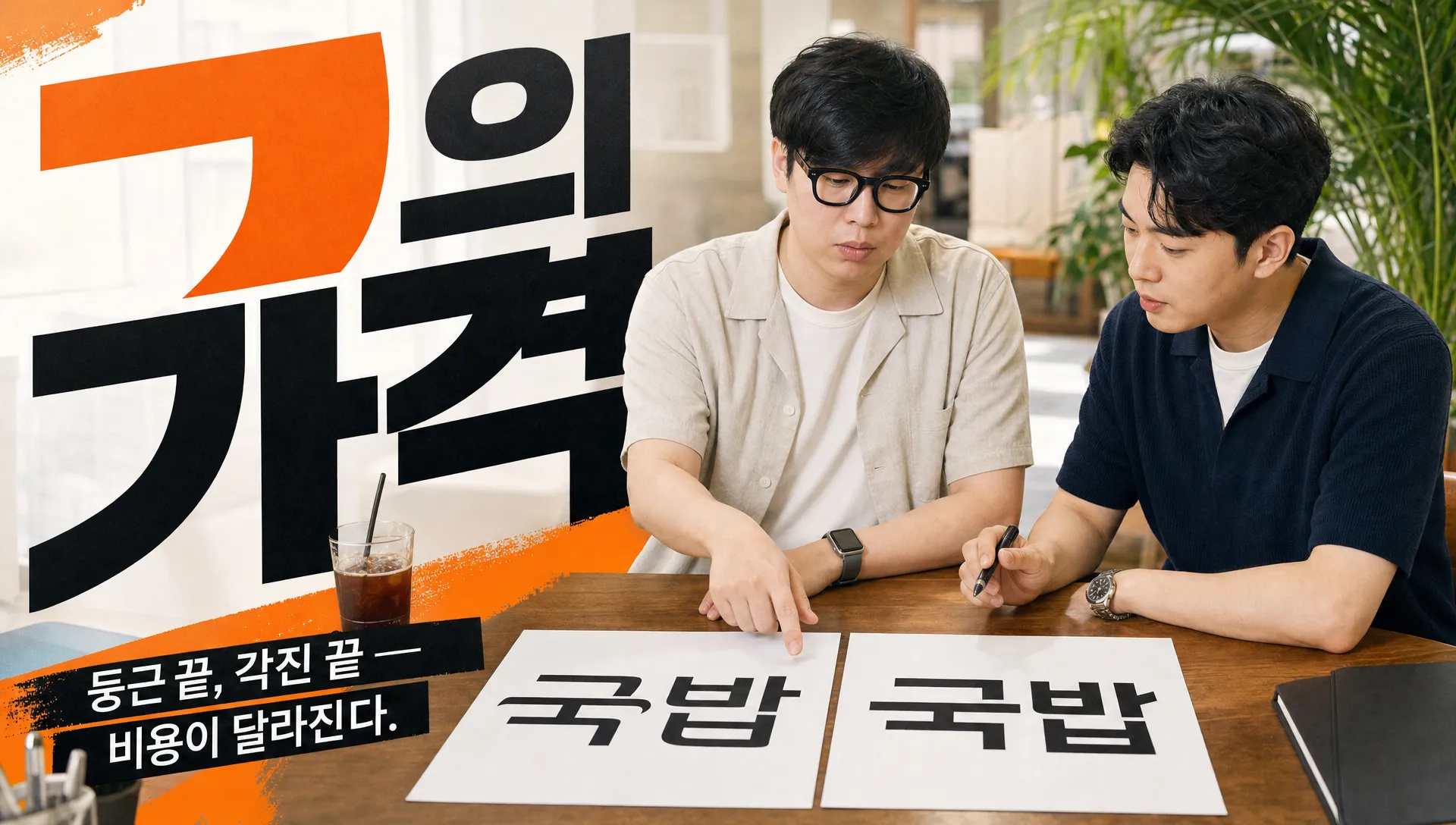
상호명은 같은데, ‘국밥집’의 ㄱ 끝을 둥글게 하느냐 각지게 자르느냐로 가격표가 바뀝니다.
왜 글씨체만 골랐는데 비용이 달라질까요?
로고 제작 비용이 30만원대에서 끝나는 경우는 보통 방향이 단순합니다. 사용 가능한 폰트를 고르고, 상호명을 얹고, 간단한 배치와 색을 정리하는 정도죠. 이 방식이 나쁜 건 아닙니다. 이름이 짧고, 업종 톤이 분명하고, 간판·명함·스티커까지 크게 무리 없는 폰트를 찾았다면 충분히 갈 수 있습니다.
문제는 상호명이 폰트에 딱 맞지 않을 때 생깁니다. 예를 들어 받침이 많은 이름은 글자가 뭉쳐 보이고, ㅅ·ㅈ·ㅊ이 많은 이름은 날카롭게 튀고, ㅇ이 반복되는 이름은 괜히 귀여워 보입니다. 이때부터는 ‘폰트 선택’이 아니라 ‘글자 설계’가 됩니다. 획 두께를 줄이고, 자간을 다시 잡고, 특정 글자의 끝 모양을 고쳐야 합니다.
그래서 100만원대 견적에는 보통 이 시간이 들어갑니다. 폰트 후보 검토, 라이선스 확인, 상호명에 맞춘 글자 수정, 작은 크기 테스트, 간판·명함·SNS 프로필 적용 확인. 겉으로는 글씨 하나인데, 실제로는 브랜드가 놓일 자리 전체를 보는 일입니다.
무료폰트면 그냥 로고에 써도 될까요?
무료폰트라는 말만 보고 바로 쓰면 위험합니다. 한국저작권위원회가 배포한 ‘글꼴 파일 저작권 바로 알기’ 자료를 보면, 글자 모양 자체와 폰트 파일은 구분해서 봐야 합니다. 특히 폰트 파일은 컴퓨터프로그램 저작물로 다뤄질 수 있습니다. 그러니까 “무료로 받았다”와 “내 가게 로고로 써도 된다”는 같은 말이 아닙니다.
제가 견적 전에 꼭 보는 건 네 가지입니다. 상업적 이용 가능 여부, CI·BI 사용 가능 여부, 수정 가능 여부, 웹·인쇄·간판 출력 범위입니다. 공유마당 안내에도 폰트마다 조건이 다를 수 있고, 일부는 기업 로고나 브랜드 상징 제작을 제한한다고 나옵니다. 결국 싼 폰트를 쓰는 게 절약이 아니라, 확인 안 한 폰트를 쓰는 게 비용 폭탄이 될 수 있습니다.
반대로 쓸 수 있는 폰트도 있습니다. 전자신문은 한국저작권위원회의 KCC간판체를 소개하며, 소상공인들이 POP·로고·간판 등에 활용할 수 있도록 공개된 글꼴이라고 전했습니다. 저는 이 대목이 현실적이라고 봅니다. 처음부터 용도가 넓은 폰트를 고르면 디자인비가 줄어들 수 있습니다. 단, 그래도 상호명에 어울리는지는 별개의 문제입니다.
글자를 어디까지 고치면 견적이 올라갈까요?
폰트를 그대로 쓰면 빠릅니다. 하지만 그대로 쓴 로고는 다른 가게 이름으로 바꿔도 어색하지 않은 경우가 많습니다. 그게 가장 큰 약점입니다. 내 상호명만의 리듬이 없다는 뜻이니까요.
저라면 먼저 글자 수를 봅니다. 두 글자는 힘이 세지만 조금만 틀어져도 어색합니다. 네 글자는 안정적이지만 평범해지기 쉽습니다. 여섯 글자 이상은 자간을 잘못 잡으면 간판에서 한 덩어리로 뭉칩니다. 여기서 획을 줄일지, 폭을 좁힐지, 받침을 정리할지 결정합니다.
특히 작은 크기에서 버티는지가 기준입니다. 명함 한쪽, 네이버 플레이스 썸네일, 배달앱 목록, 인스타 프로필에 넣었을 때 읽혀야 합니다. 예쁜 글씨보다 오래 가는 글씨가 먼저입니다. 마크에서 워드마크를 볼 때도 처음엔 크게 보지 않고, 일부러 작게 줄여서 이름이 남는지 확인합니다.
견적서를 받을 때 무엇을 물어봐야 할까요?
“폰트 포함인가요?”보다 더 정확한 질문이 있습니다. “이 로고에 사용한 폰트의 라이선스 범위와 증빙을 받을 수 있나요?” 이 한 문장만 물어도 작업자가 글자 문제를 얼마나 챙기는지 보입니다.
두 번째는 “상호명 글자를 직접 수정하나요, 폰트 그대로 쓰나요?”입니다. 폰트 그대로 쓰는 작업과 획·자간·비율을 만지는 작업은 시간이 다릅니다. 그러니 금액 차이가 나는 게 이상한 게 아닙니다. 오히려 두 작업을 같은 값으로 말하면 무엇이 빠졌는지 봐야 합니다.
세 번째는 결과물 범위입니다. 원본 파일, 흑백 버전, 가로형·세로형, 작은 크기용 버전까지 포함되는지 확인하세요. 글자는 크게 볼 때보다 작게 쓸 때 문제가 더 많이 드러납니다. 로고는 간판 한 번으로 끝나는 그림이 아니라, 계속 복사되고 줄어들고 옮겨 다니는 이름입니다.